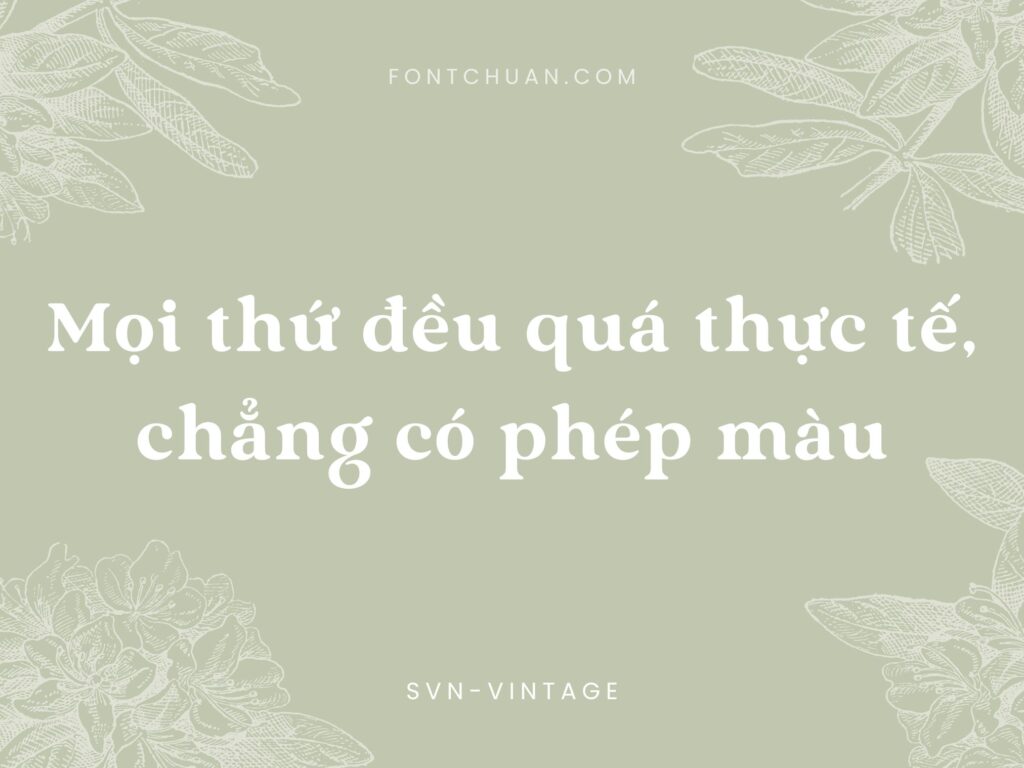
Font SVN Vintage Việt Hóa
Font SVN Vintage là phiên bản Việt hóa của kiểu chữ Vintage, được thực hiện bởi Styleno.1 Fonts. Vintage là một kiểu chữ serif hiển thị với độ tương phản vừa phải, hoàn hảo cho các dự án thương hiệu, thiết kế logo, thiệp cưới, bài đăng trên mạng xã hội, quảng cáo, bao bì sản phẩm và nhiều ứng dụng khác. Font này mang đến cảm giác cổ điển nhưng vẫn hiện đại, giúp tạo điểm nhấn độc đáo trong thiết kế.
SVN Vintage lý tưởng cho các dự án thiết kế yêu cầu sự thanh lịch và cổ điển, như thiết kế logo, tiêu đề, bao bì sản phẩm và các ấn phẩm quảng cáo. Các ngành nghề như quảng cáo, thiệp cưới và bất động sản có thể tận dụng font này để tạo điểm nhấn trong thiết kế. Ngoài ra, font cũng phù hợp cho các sự kiện như Tết, Giáng sinh, Valentine và các lễ hội khác.